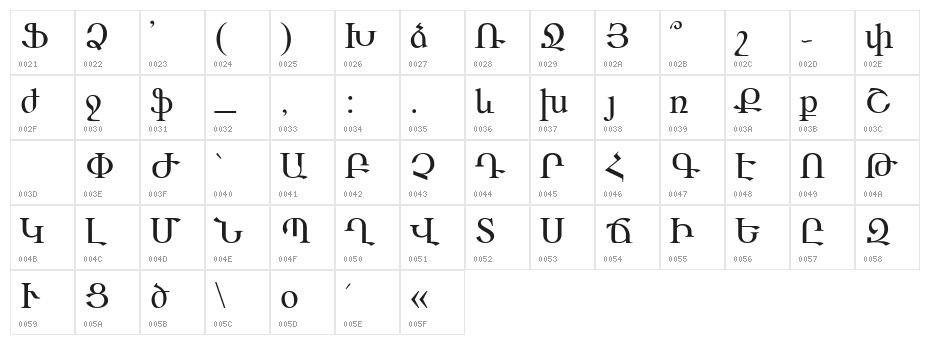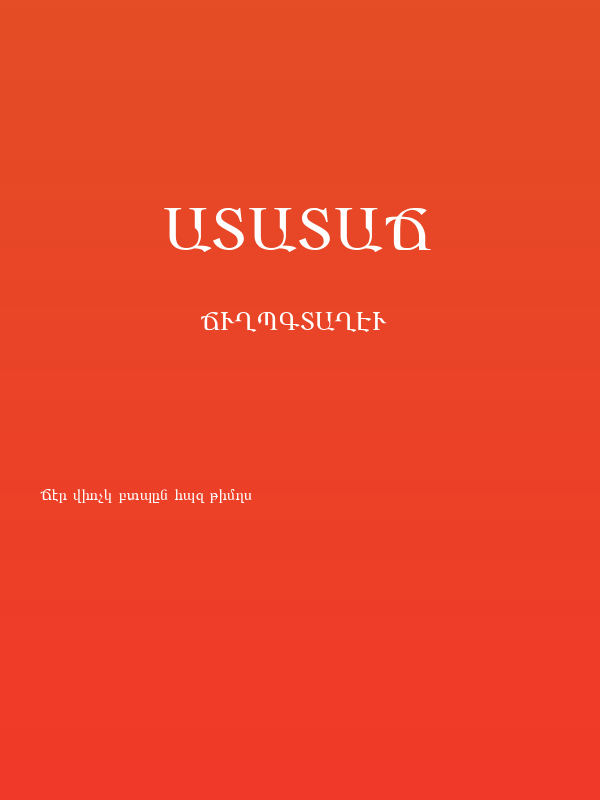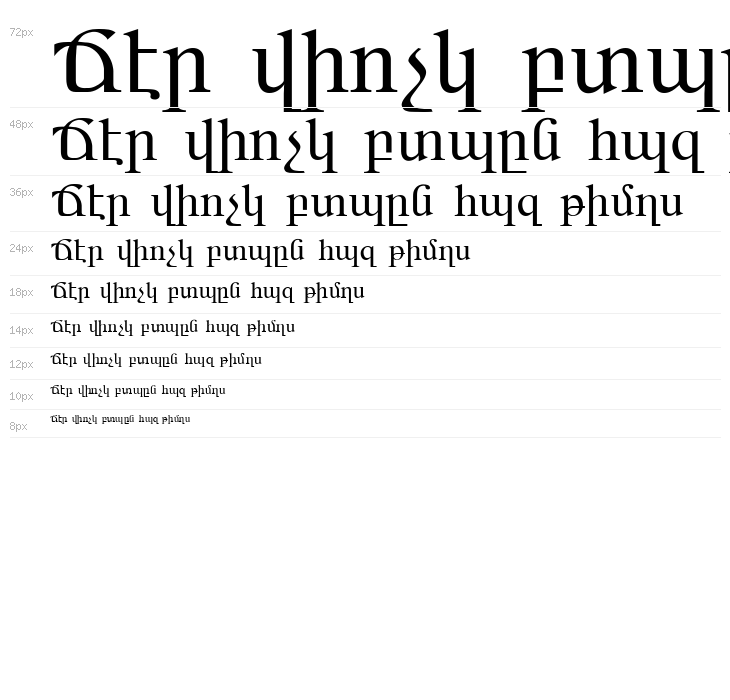
ARARAT Font
| Gesamtstil | Classic |
| Anwendungsfall | Headlines, Body text, Logos |
| Vorgeschlagene Projekte | This font is perfect for editorial design, branding projects, book covers, and formal invitations due to its elegant and classic style. |